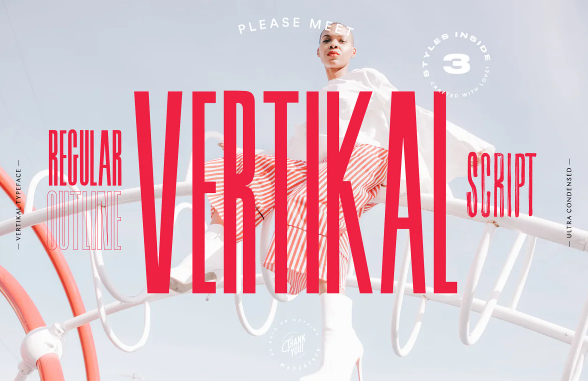
[Creativemarket] Vertikal Font (2021)
Представляем: Vertikal -Высокий конденсированный шрифт с засечками, представленный в 3 стилях.
Если вы ищете буквы с характером, Vertikal - идеальный вариант. Это запоминающийся, сильный и элегантный шрифт. Вы можете смешивать и сочетать стили Outline и Regular, чтобы создать что-то очень свежее и современное. Шрифт Brush Script - это "плохой мальчик" коллекции, но при этом очень стильный.
ПРИМЕНЕНИЯ
Эта коллекция идеально подходит для заголовков, цитат, обложек журналов, редакционного дизайна, печатных плакатов, вывесок, оформления витрин и многого другого.
Vertikal Regular
Vertikal Outline
Vertikal Brush Script